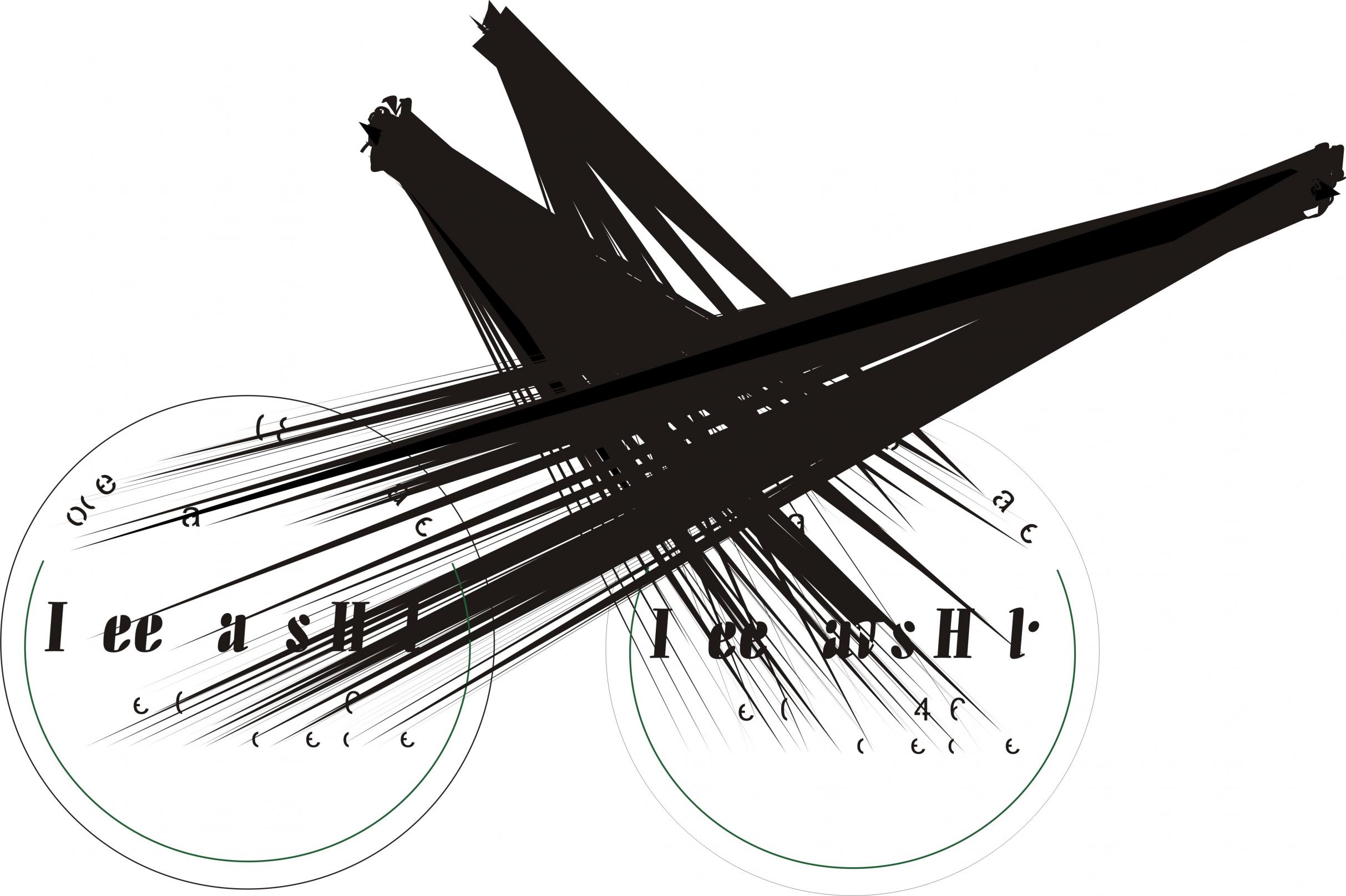
Schneidbare Schriftart gesucht
ich brauche eure Hilfe. Und zwar bin ich auf der Suche nach einer Schriftart, die verhindert, dass beim ausschneiden der Buchstaben, die Füllung rausfällt.
Und zwar bin ich dabei ein Schriftlog für eine Wasserstrahlarbeit anzufertigen. Das Problem ist, wenn man zum Beispiel ein B oder ein O ausschneidet, fällt die von den Linien eingeschlossene Fläche raus.
Deswegen haben ich für normal Aufträge mir bereits ein Bibliothek mit Buchstaben gebaut, in der das B nicht komplett durchgezogen ist und somit die Flächen des B's nicht herausfallen.
Da jedoch diesmal das Logo krumm ist, bin ich auf der Suche nach einer Schriftart, mit der ich in meinem Grafikprogramm schreiben kann.
Bei meiner bisherigen Suche bin ich auf die Font "Bauhaus 93" gestoßen. Doch diese Schriftart passt nicht zum Logo.
Daher suche ich eine Schriftart ähnlich "Calibri"
Wie finde ich solch eine Schriftart?
in dem du die seiten durchsuchst, auf denen es kostenlose schriftwarten gibt.
in welchen grafikprogramm erstellst du die Vorlage ?
ist es ein vektor-grafik-programm?
in denen kannst du ja die schrift "auflösen", also in pfade umwandeln, die du dann entsprechend nachbearbeitest.
ich habe bereits Fonteiten durchgesehen. Da habe ich bisher keine gefunden, aber Stencil Font ist schon einmal ein Anfang. Diese ist jedoch zu Hart. Calibri ist da doch weicher.
Als Grafik Programm nutze ich Adob Illustrator oder Corel Draw X3. Da ich selbst nicht häufig mit Grafikprogrammen Arbeite und nur die Standards Beherrsche, meine Frage. Ist die Arbeit des Auflösens eine komplizierte?
mit den von dir genannten kenne ich mich nicht aus, hab so was mal mit inkscape gemacht, und da waren es ein paar Mausklicks zum auflösen.
ich glaube aber nicht, dass es mit deinen kompliziert ist.
versuchs mal so:
Text markieren, dann Menü Anordnen in Kurven konvertieren
okay, eine Möglichkeit Buchstaben zu verändern habe ich jetzt gefunden. Jedoch habe ich das Problem, dass das nicht sehr gleichmäßig erfolgt.
Daher bin ich weiter auf einer Schriftart ähnlich Calibiri jedoch mit dem Unterschied, dass die Linien nicht geschlossen sind und somit die Flächen wie die beim A oder B nicht herausfallen.
ich weiß, dass das ein Typ ist. Habe auch bereits auf einer anderen Seite die ganzen Unterarten angesehen.
Die sind alle zu militärisch bzw. manch mal ausgefranzt oder verwaschen, dass kann ich leider nicht gebrauchen.
was für einen text brauchst du denn ?
ich schreib den dir in Calibri und verändere den so, dass er schneidtauglich ist (sofern es nicht zuviel text is)
ist der text gerade, oder bogenförmig ?
der Text ist Bognförmig... Ich würde das Logo morgen erstellen - in Calibri - und dir dann zukommen lassen.
ist der text lang ? wie viele Buchstaben müssten bearbeitet werden ?
Insgesamt sind es 70 Zeichen, jedoch die Zeichnen die Bearbeitet werden müssen sind "nur" 26
Ich werde das Logo wahrscheinlich heute Abend noch fertig stellen. Dann lass ich es dir zukommen und du sagst mir deine Meinung dazu.
am besten wäre es wenn du in einem separaten Bild, bei den verschiedenen Buchstaben die Stellen markierst, wo der Steg sein soll, weil da gibt es ja mehrere Möglichkeiten.
wie breit soll der Steg sein?
wie groß wird das ganze?
So hier kommt die RAR Datei.
Darin enthaltn zwei verschiedene Versionen, einmal als Kurven SVG und einmal als Text SVG. Ich weiß nicht, ob es darin einen Unterschied gibt.
Desweiteren habe ich die Datei als CDR (Corel Datei) sowie ein JPEG angehängt.
Das JPEG ist mit roten Linien versehen. Diese sollen die Stellen zeigen, an denen die Buchstaben aufgebrochen werden sollen.
Im Allgemeinen sollen die Stege min. 1 Millimenter betragen. Wenn du sie also so breit machst wie die Linienstärke des Buchstabens selber, genügt es mir um damit zu arbeiten.
In der Mitte des Logos findest du die Worte: "Ideen aus Holz". Diese sind in der Schriftart Allegro BT geschrieben. Dort bitte ich dich, den aufbruch zu erweitern, damit der komplette dünne Steg am oberen Teil des Buchstabens verschwindet.
Wie kann ich dir für deine Arbeit danken?
Edit: Das ganze wird am Ende 40 - 60 mm im Durchmesser. Du musst dir deswegen keinen Stress machen. Schick es mir einfach, wenn du fertig bist.
habs mal bearbeitet, hab 2 Versionen gemacht (nur die 4 unterscheidet sich)
gucks dir mal an, ob das so passt. die Durchbrüche hab ich pi mal Daumen in die Mitte der Buchstaben gesetzt.
einen Schreibfehler hab ich auch korrigiert.
also ich habe seit gestern die Änderungwünsche bekommen.
Diese sehen unter anderem vor, dass Falk Schilb in Tischlerei Schilb umgewandelt wird und etwas von mir, die Ö-Punkte sind beschnitten wurden beim Buchstaben teilen.
kannst du mir bitte dieses Logo bearbeiten, so dass die geschlossenen Flächen nicht herausfallen? Und zwar nach der rechten Variante. Also die 4 nur mit einem Schnitt getrennt.